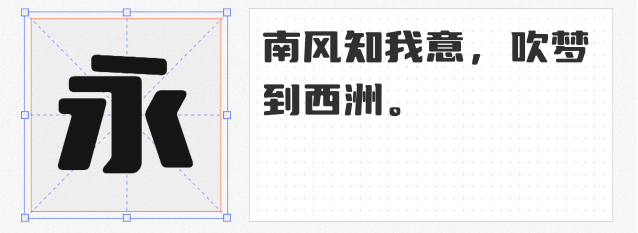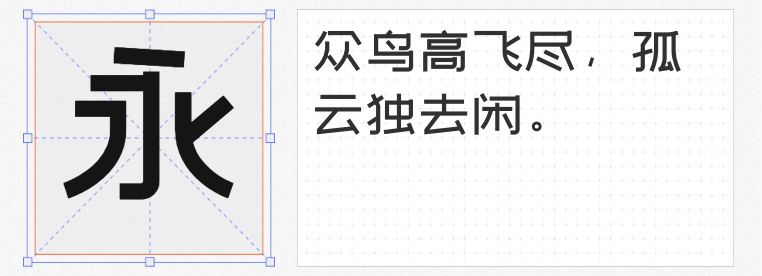
当2025年的尾声渐近,设计圈的“新年企划”已悄然启动。无论是筹备2026年的品牌视觉升级、节日营销物料,还是为跨年活动定制创意海报,一款契合氛围的字体总能成为点睛之笔。然而,商用场景下的字体选择常面临版权限制与风格同质化的双重挑战——如何在不增加成本的前提下,让设计既合规又脱颖而出?
本文精选4款免费可商用的创意字体,涵盖多元风格,既有适配传统年味的书法体,也有突破常规的潮流设计。提前收藏这份清单,让文字成为你2026年创意战役中的秘密武器,轻松打造令人过目难忘的视觉记忆点!
1. 站酷快乐体
由站酷网发布的站酷快乐体,以圆润的笔画和夸张的弧度构建出活泼俏皮的视觉效果。其字形如跳跃的音符,适合儿童品牌、节日海报或年轻化产品包装。
2. 优设标题圆
作为优设标题黑的升级版,优设标题圆通过将尖锐转角转化为圆润弧线,实现了力量感与亲和力的平衡。其笔画粗细对比强烈,中宫紧凑,特别适合科技类、运动类品牌的标题设计。
3. 站酷文艺体
由设计师刘兵克主导开发的站酷文艺体,以略扁的字形结构营造出独特的文艺气质。笔画粗细统一却通过细节设计打破单调:圆角处理赋予温柔感,"口"字右上角的竖线创新增强辨识度,撇捺的曲直对比则带来动态韵律。这款字体在书籍封面、文化类海报设计中表现尤为出色,能精准传递淡雅高级的审美格调。
4. 斗鱼追光体2.0
专为电竞品牌斗鱼开发的追光体2.0,通过转角圆弧处理和包围结构切口设计,打造出科技感与速度感并存的视觉效果。中宫开阔的字体结构确保远距离可读性,适合游戏直播界面、科技产品宣传等场景。其独特的笔画切割设计,在暗色背景中搭配发光效果能产生强烈的视觉冲击。